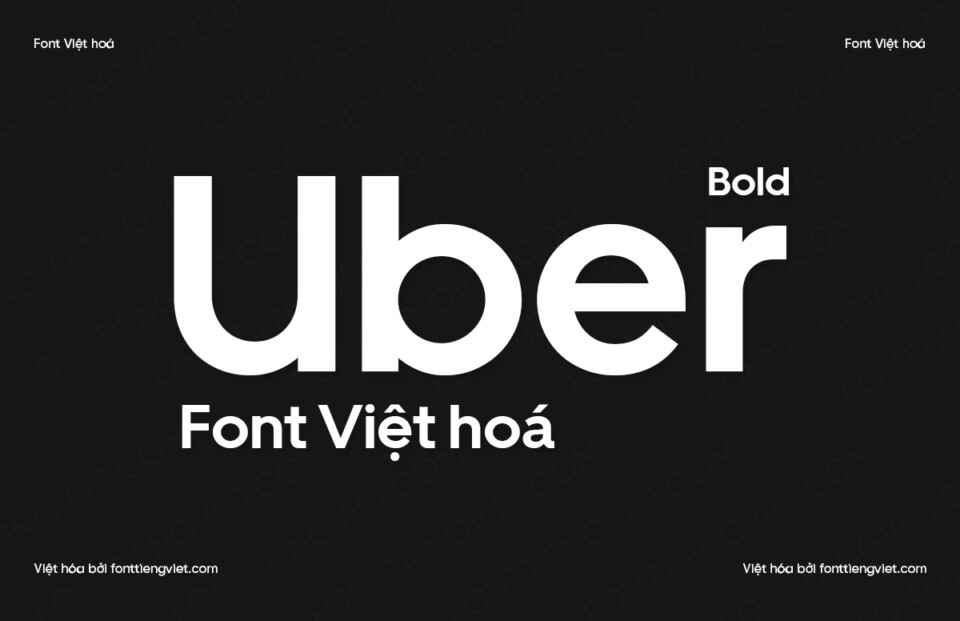
Font Việt hóa 1FTV VIP Uber Move Bold
Font Việt Hóa 1FTV VIP Uber Move Bold – Lựa Chọn Hoàn Hảo Cho Thiết Kế Hiện Đại
Trong thế giới đồ họa nói chung và môi trường giáo dục nói riêng, việc lựa chọn một phông chữ chất lượng đóng vai trò cốt lõi để truyền tải thông điệp hiệu quả. Đối với các thầy cô giáo và các bạn học sinh đang tìm kiếm sự đột phá cho bài giảng hay báo tường, Font Việt hóa 1FTV VIP Uber Move Bold chính là một giải pháp lý tưởng. Đây là bộ chữ mang hơi thở hiện đại, được Việt hóa chuẩn 100%, giúp người dùng hoàn toàn yên tâm sáng tạo mà không lo lỗi hiển thị dấu câu.
Ưu Điểm Nổi Bật Của 1FTV VIP Uber Move Bold
Bộ phông chữ này ghi điểm mạnh mẽ nhờ những đặc tính thiết kế vượt trội, đặc biệt hữu ích trong công tác giảng dạy và học tập:
• Thiết kế mạnh mẽ, rõ ràng: Sở hữu các nét chữ dày dặn, hình khối dứt khoát cùng khoảng cách ký tự (kerning) được căn chỉnh vô cùng khoa học.
• Tối ưu hóa khả năng đọc: Nhờ sự rõ nét, học sinh có thể dễ dàng theo dõi và tiếp thu kiến thức trên bảng tương tác hoặc máy chiếu mà không bị mỏi mắt.
• Thẩm mỹ hài hòa: Sự kết hợp khéo léo giữa nét bo tròn mềm mại và các góc cạnh dứt khoát mang lại một tổng thể vừa chuyên nghiệp, hiện đại, lại vừa gần gũi với môi trường học đường.
Tính Ứng Dụng Linh Hoạt Trong Môi Trường Học Đường
Không chỉ dừng lại ở các thiết kế đồ họa thông thường, Uber Move Bold chứng minh tính đa năng tuyệt vời của mình qua nhiều ấn phẩm khác nhau:
• Bài giảng trực quan: Ứng dụng làm tiêu đề (Heading) nổi bật trên các slide PowerPoint, tạo điểm nhấn thu hút sự chú ý của cả lớp học.
• Ấn phẩm truyền thông: Rất phù hợp để thiết kế băng rôn sự kiện, báo tường, bìa sổ tay học sinh.
• Khen thưởng: Tạo ra những mẫu giấy khen, bằng khen trang trọng và đẹp mắt.
Tổng Kết
Tóm lại, việc ứng dụng Font Việt hóa 1FTV VIP Uber Move Bold sẽ giúp các dự án sáng tạo và tài liệu giáo dục của bạn trở nên chuyên nghiệp và ấn tượng hơn bao giờ hết.